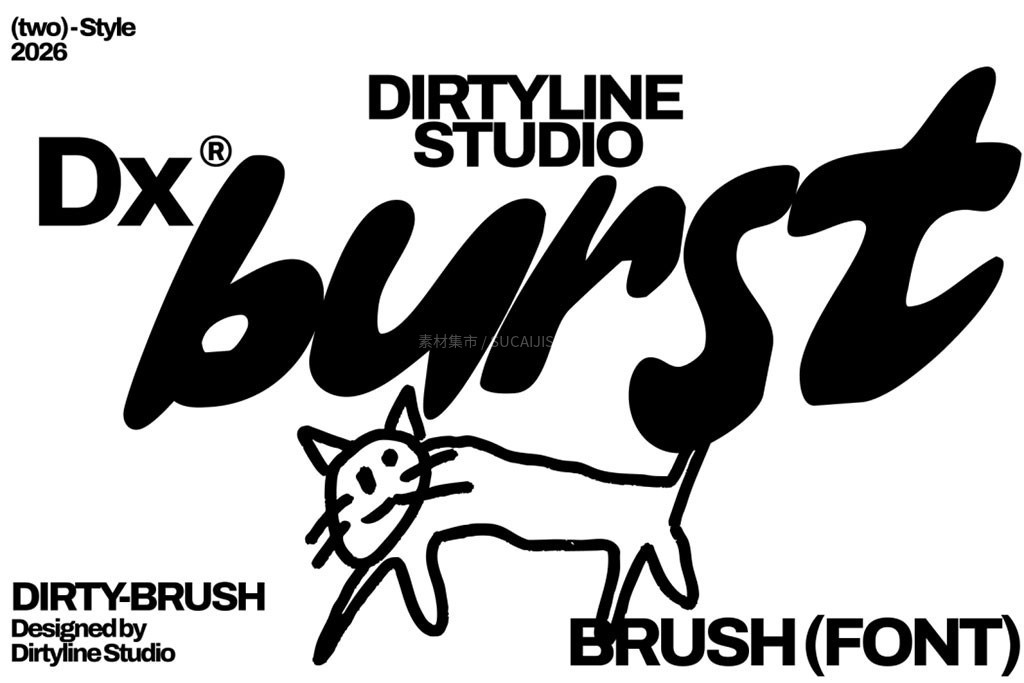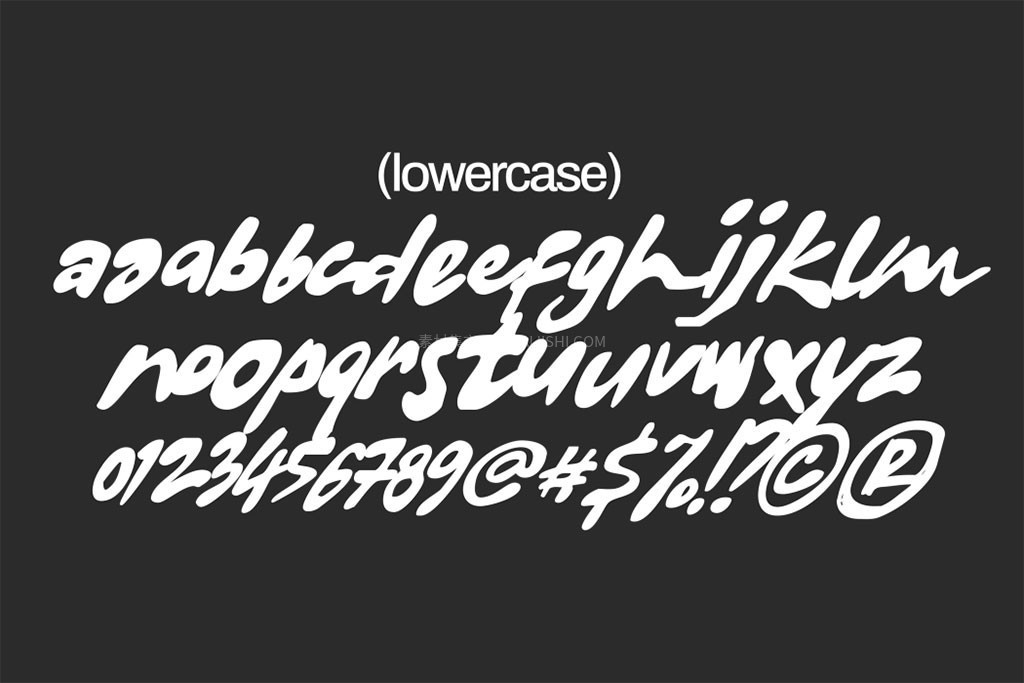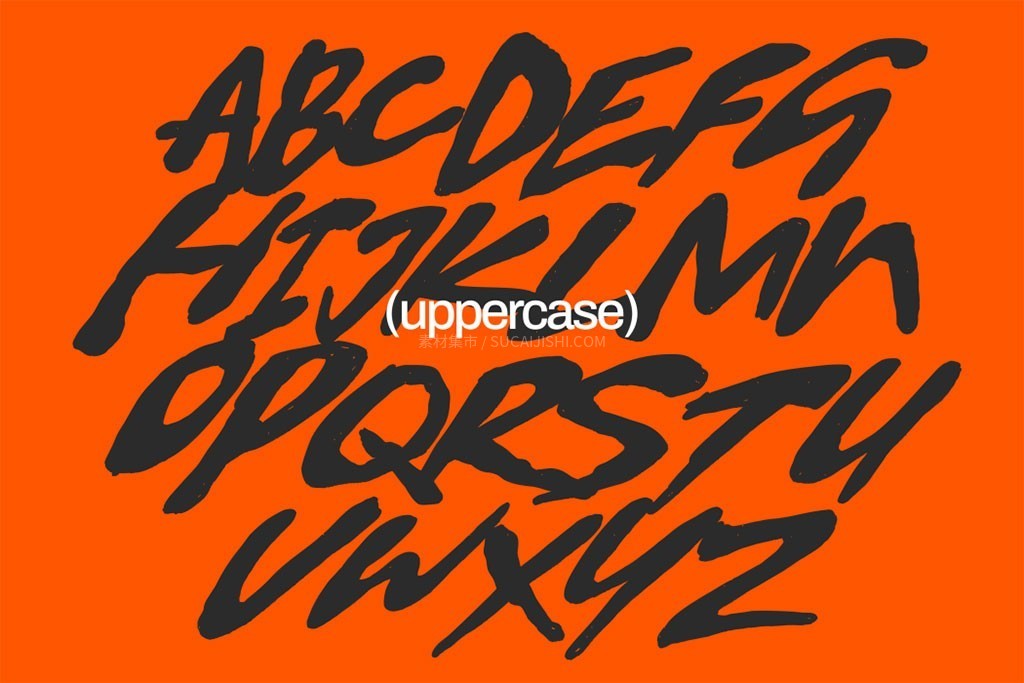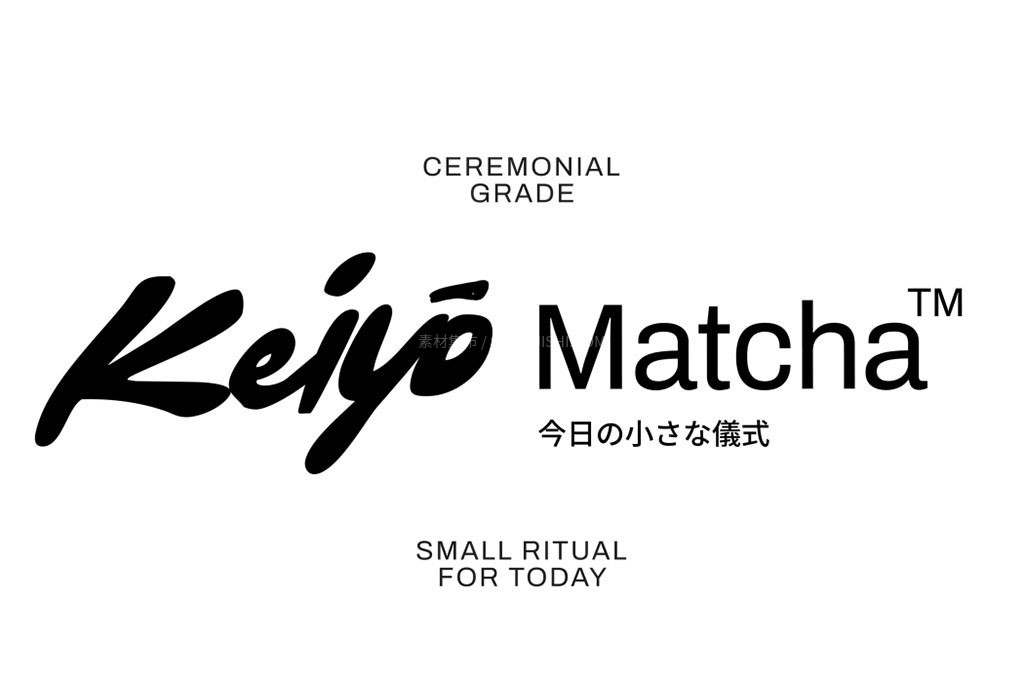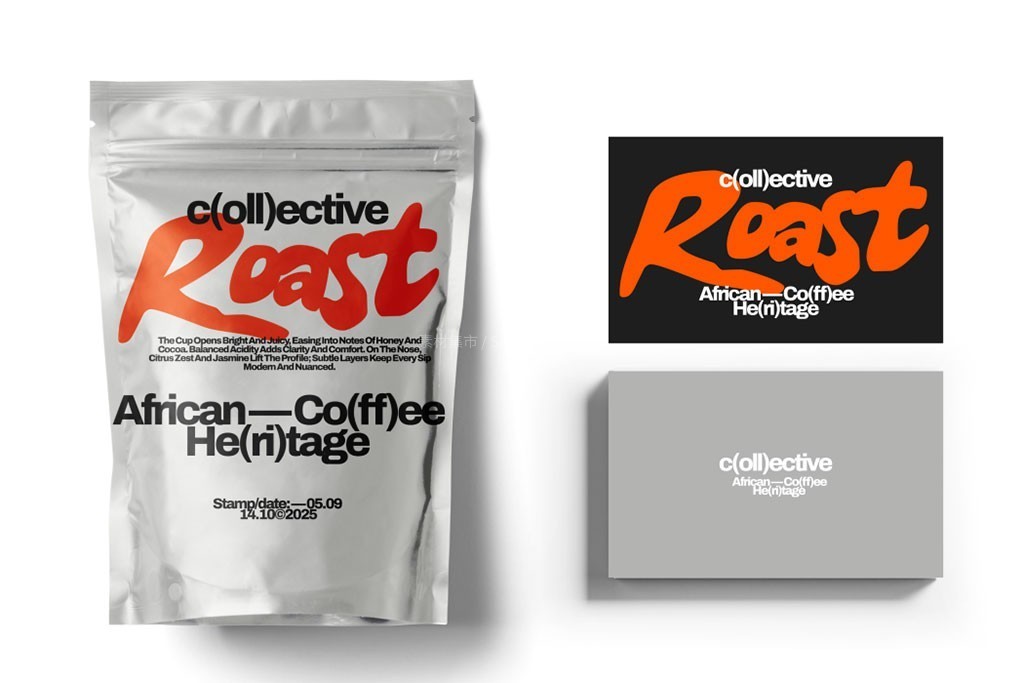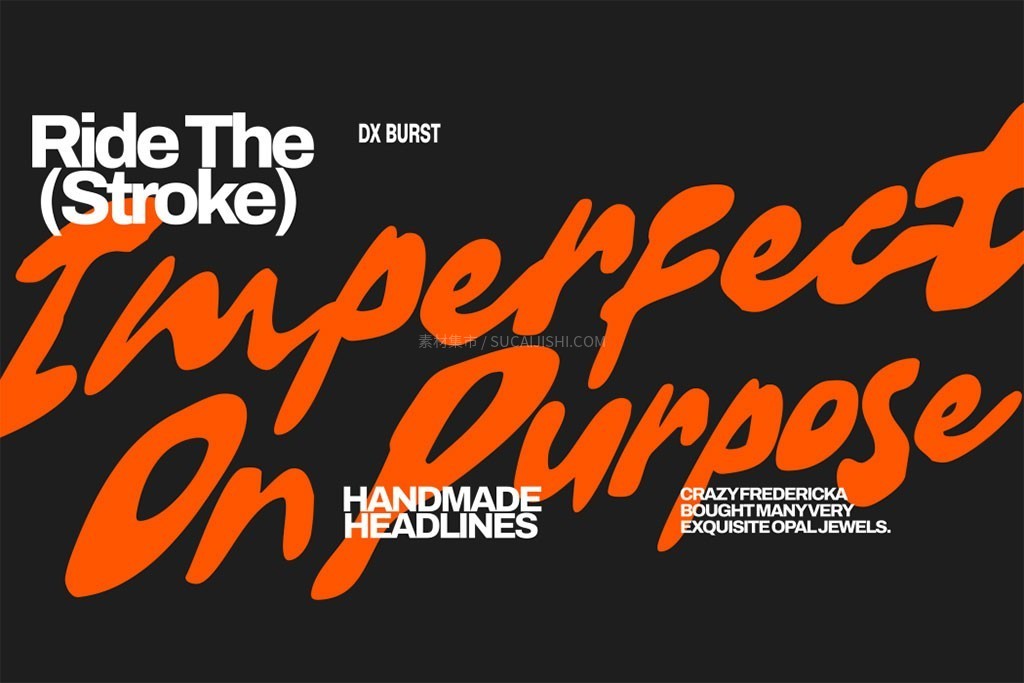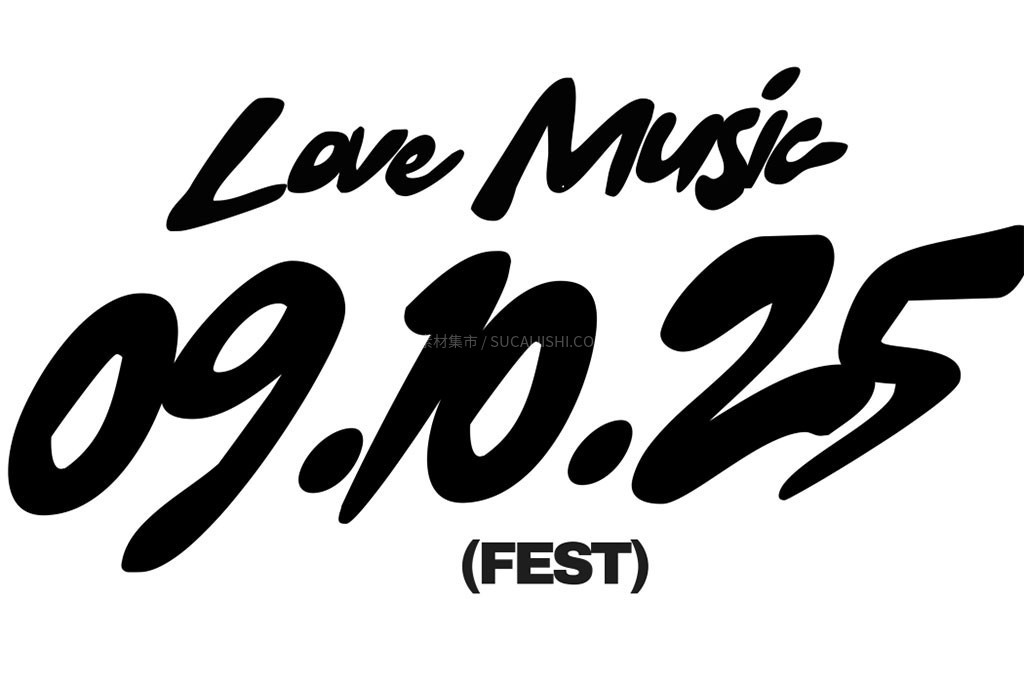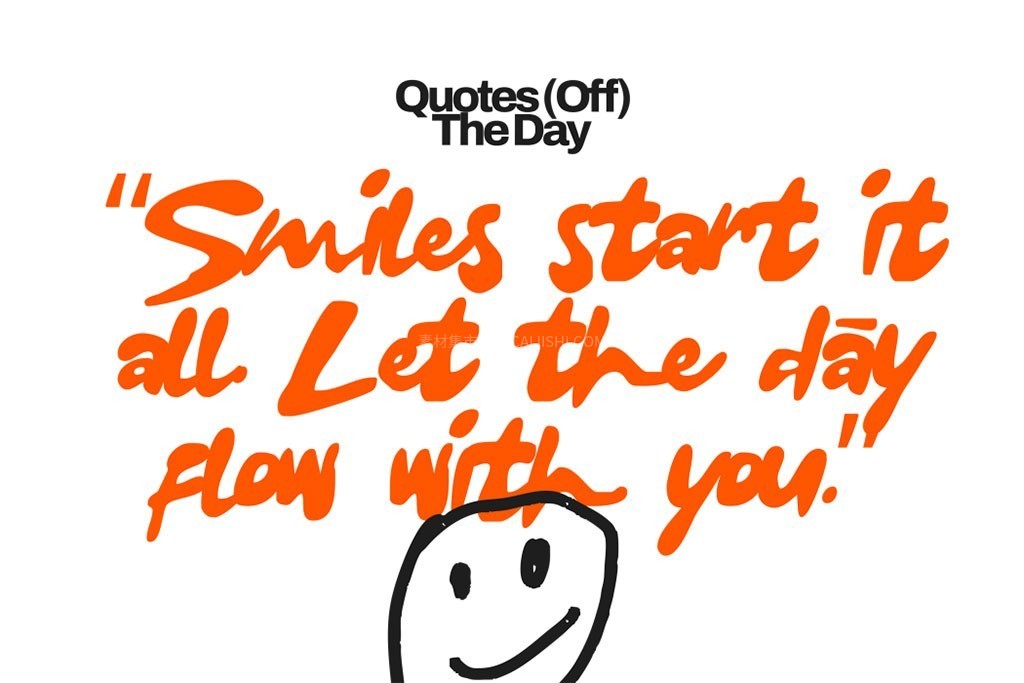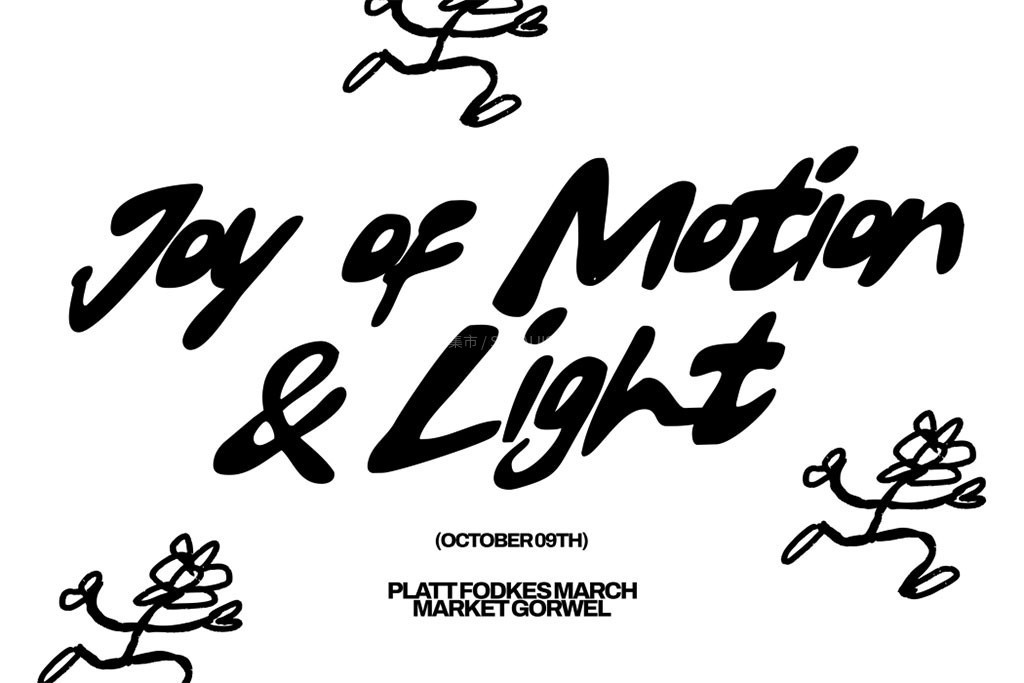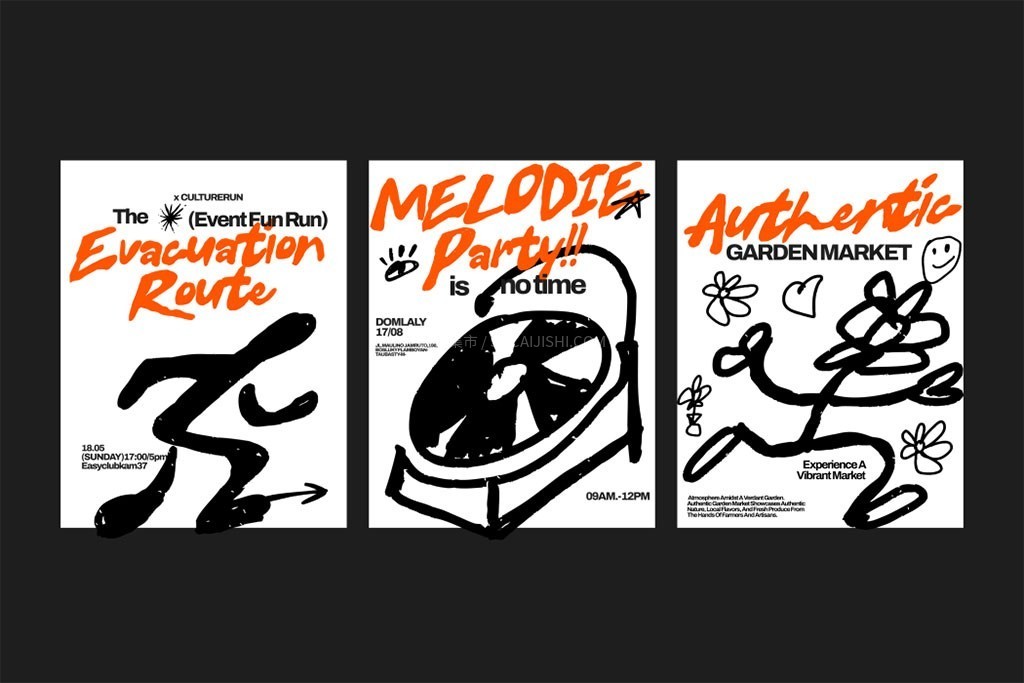
Dx Burst 街头感拉满手刷笔刷英文字体
这套由 Dirtyline Studio 设计的 DX Burst 字体真的绝了!它是一款极其大胆且充满表现力的笔刷字体,自带那种粗犷又随性的手绘笔触,把“不完美”的张扬个性展现得淋漓尽致。如果你想让设计作品瞬间抓住眼球,选它准没错!字体贴心地包含了两种款式,让你能在相对可控和极其狂野的情绪之间灵活切换。强烈建议大家在做大尺寸标题时使用它,能把真实的纹理和笔触细节完美放大,搭配极简的无衬线字体,视觉冲击力直接拉满,都市实验感满分!